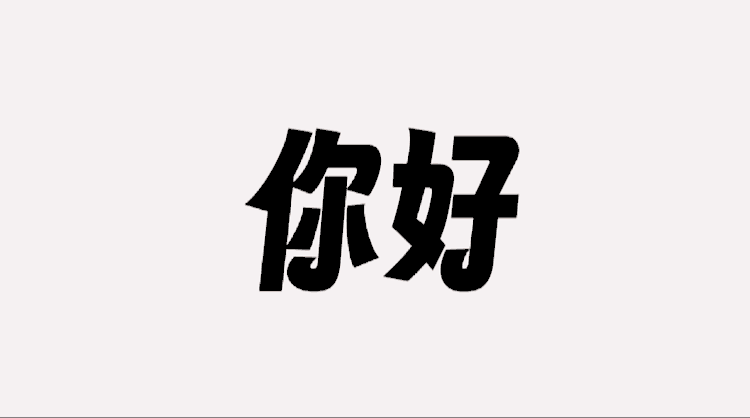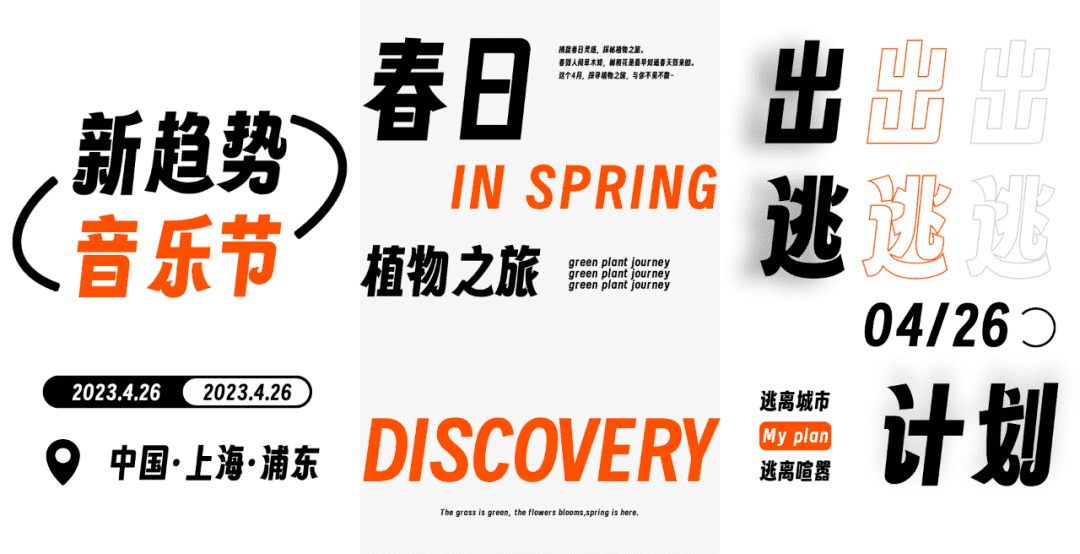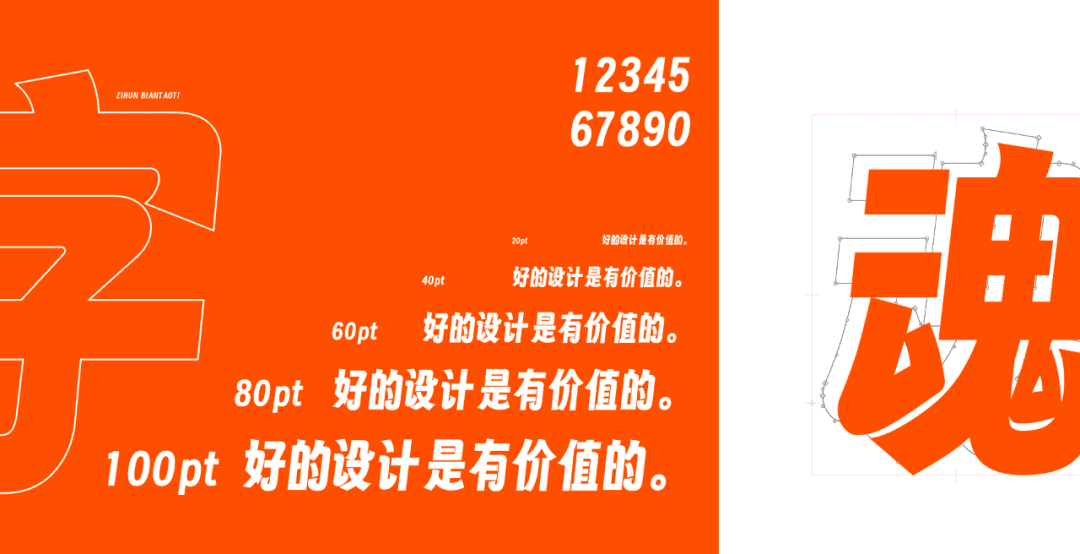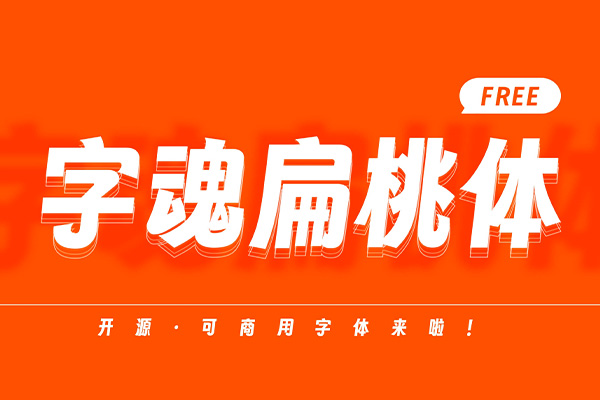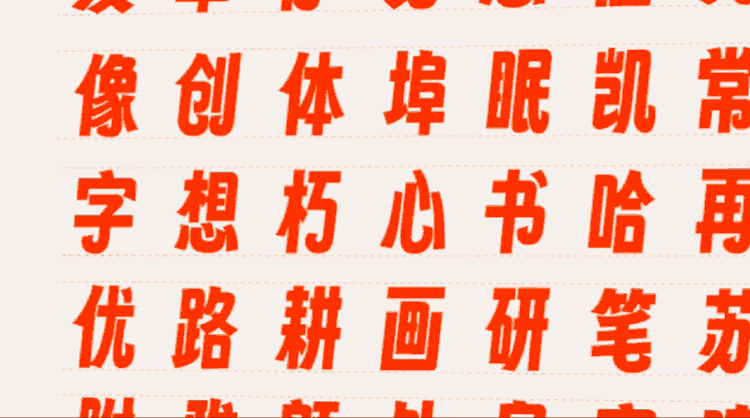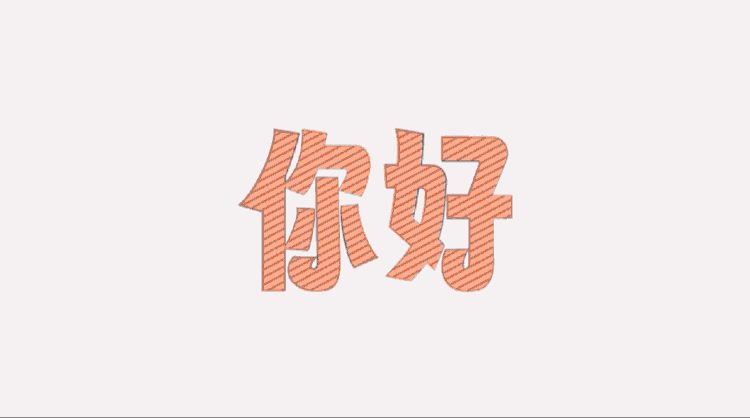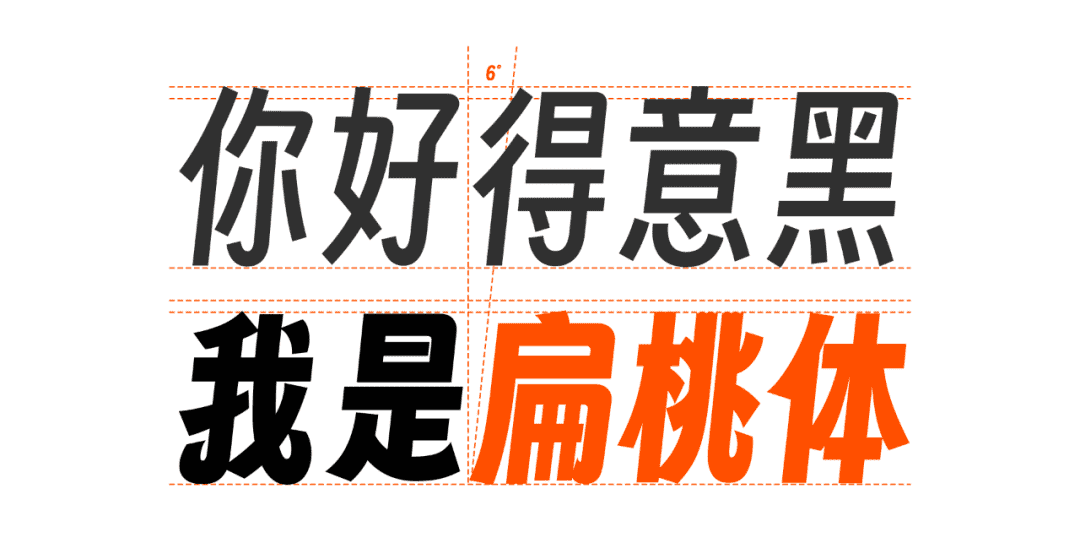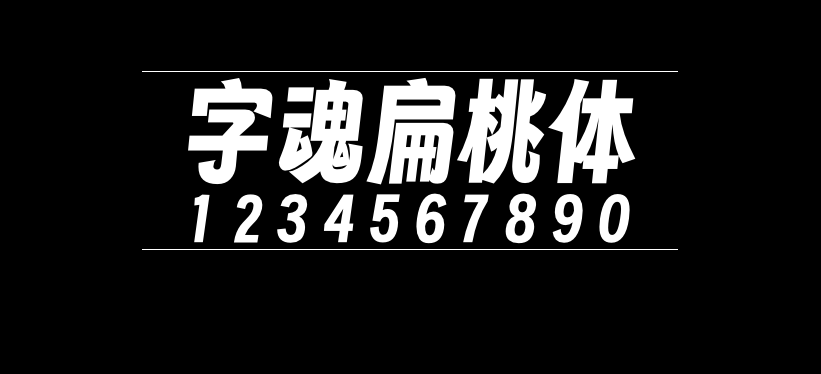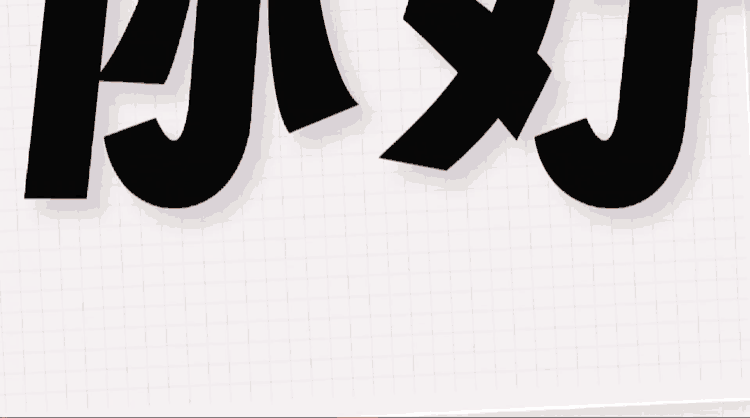
字魂扁桃体
字魂扁桃体是字魂网推出的第一款免费商用字体,该字体基于oooooohmygosh老师与锚钨团队发布的免费商用字体「得意黑」进行二次创作,发布开源字体「字魂扁桃体」,同样是开源并永久免费商用,提供给所有用户。
字体解析
我们想在得意黑的基础上做出一款更有力度且个性十足的创意字体。
通过不断的尝试努力……
字魂扁桃体
这款字体继承自得意黑标志性特点:
字形6°到8°的倾斜,挺拔高挑,特定笔画保持弯弧处理。
它精神饱满,温和又时髦。
字魂扁桃体
我们在得意黑基础上加粗字重,且略微加宽字身,提升整体重量感。
字魂扁桃体
特色喇叭口设计让得意黑的标志性微笑弧度“卷起来了”。
这个创意让整个字体充满活力,个性鲜明。
得益于汉字结构丰富,喇叭口小卷产生了无限可能。
类似的创意还有很多……
我们不遗余力地为每个笔画寻找最适合并有趣的处理方式。
字魂扁桃体
这些变化让字体有了新的功能性,比如在现代媒介、商业宣传,
这些场景能更好适配,因为它更醒目且独特了。关于新字体的命名:
oooooohmygosh老师在发布得意黑时,曾提到,
欢迎字体设计师们对得意黑进行二创并命名XX体,他开了个玩笑,说叫扁桃体。
字魂扁桃体
我们把这款字体做得足够有趣,也希望用创意让每个使用者能会心一笑。
我们想起了这个“梗”,于是,这套字体,它就叫:「字魂扁桃体」!
字魂扁桃体